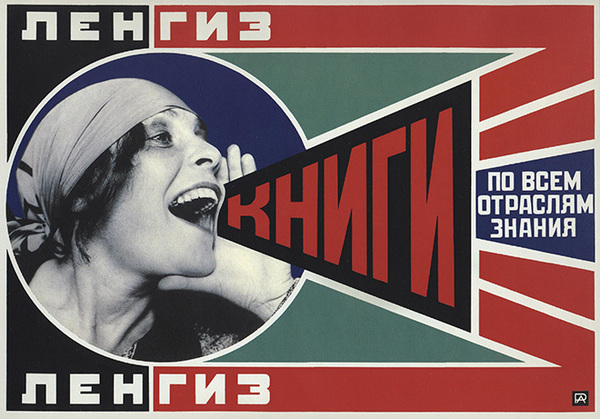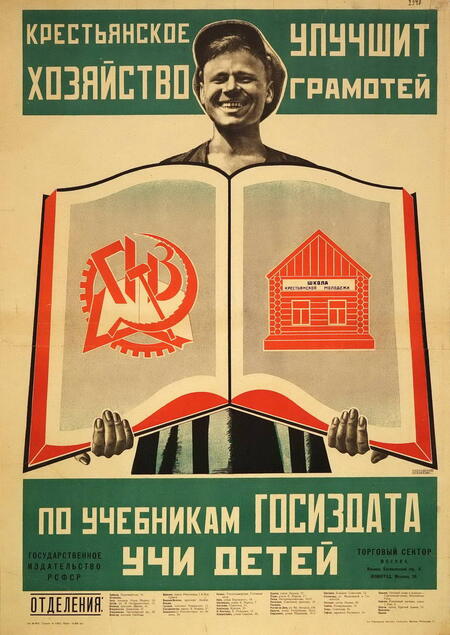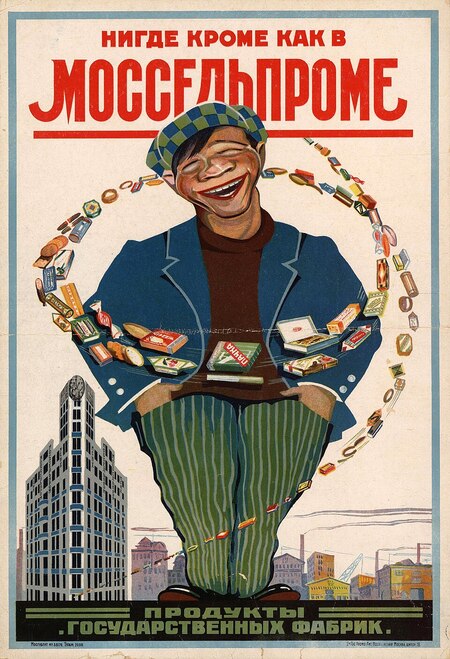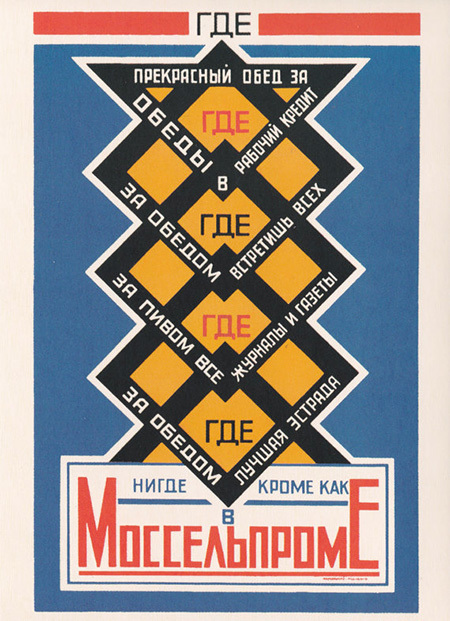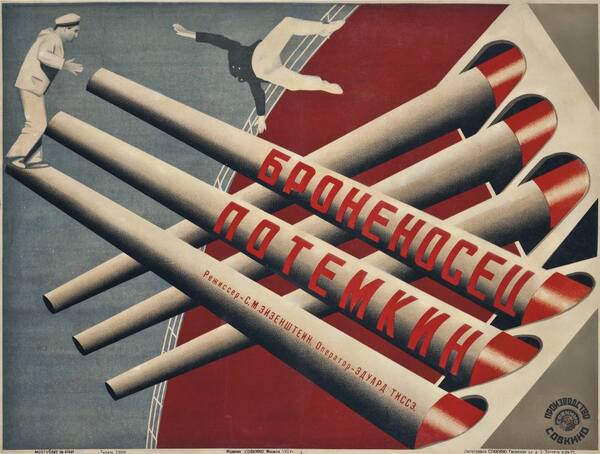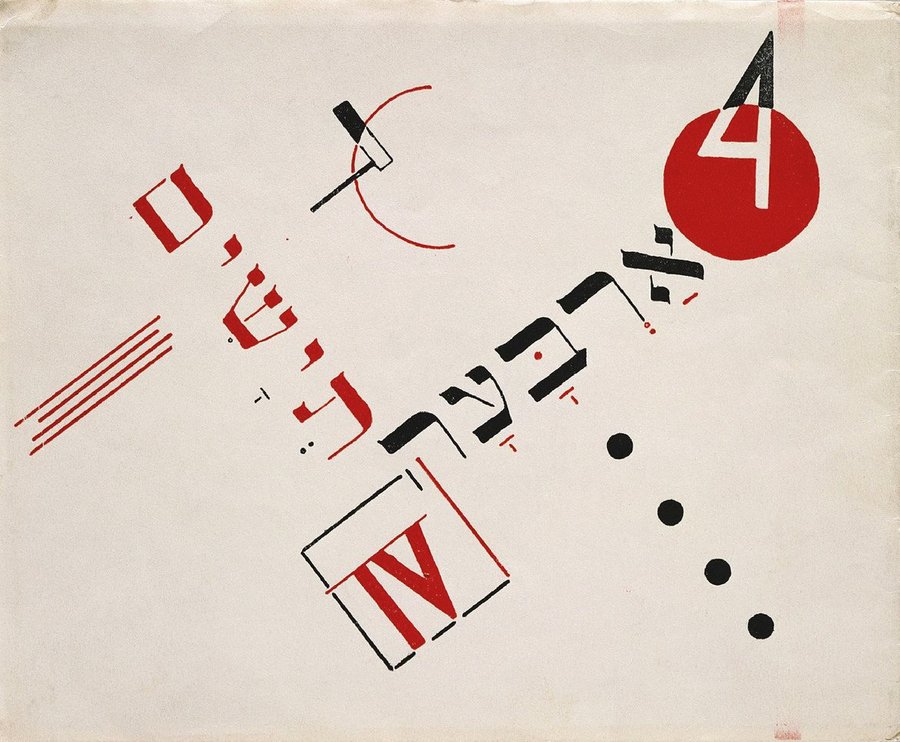
Красный шрифт: графика советского конструктивизма 1920-х гг.
[1] Введение
Эль Лисицкий, Teyashim (Four billy goats), 1922 год
После Революции 1917 года в России сформировалась потребность не только в новом политическом строе, но и в принципиально ином визуальном языке, способном отразить идеи строительства социалистического общества. Конструктивизм, возникший как авангардное художественное течение, стал ответом на этот социальный запрос, трансформировавшись из эстетического эксперимента в мощную систему графической пропаганды. Это направление радикально порвало с декоративностью предшествующих стилей, провозгласив функциональность и утилитарность главными критериями искусства. Данное исследование направлено на комплексный анализ того, как базовые принципы конструктивизма (функциональность, геометричность форм и инновационная типографика) сформировали уникальный визуальный код, определивший лицо советской графики 1920-х и начала 1930-х годов.
Актуальность темы подтверждается сохраняющимся влиянием конструктивизма на современный дизайн, что позволяет исследовать универсальные механизмы создания эффективных визуальных коммуникаций.
Основной исследовательский вопрос заключается в выявлении методов, позволивших конструктивистам создать столь эффективную систему визуальной коммуникации, способную транслировать сложные идеи нового общества массовой аудитории. Выдвигается гипотеза о том, что эта эффективность была достигнута благодаря органичному синтезу типографики, фотомонтажа и цветовой символики в единую систему графических кодов, превратившую плакат в мощный инструмент массовой пропаганды и социальной инженерии.
[1] Александр Родченко, Ленгиз: книги по всем отраслям знаний, 1925 год; [2] Александр Родченко, Обложка журнала «ЛЕФ» № 3, 1923 год
Исторический контекст исследования охватывает период Новой экономической политики (1921–1928 гг.), когда происходил расцвет конструктивистского дизайна. Именно в эти годы сформировался специфический спрос на рекламу, агитационные плакаты и оформление новой городской среды. Художественные институты, в частности ВХУТЕМАС, стали настоящими лабораториями нового искусства, где разрабатывались и апробировались революционные визуальные стратегии.
[1] Александр Веснин, Проект оформления здания ВУХТЕМАСа к 10 годовщине Октябрьской революции (эскиз), 1927 год; [2] Неизвестный автор, Фрагмент обложки журнала «Техника и жизнь № 6», 1925 год
Отбор материала для исследования основан на принципе репрезентативности — в фокусе внимания находятся канонические работы ключевых представителей движения: А. Родченко, В. Степановой, Эля Лисицкого, братьев Стенбергов. Их творчество наиболее полно отражает основные тенденции и художественные открытия эпохи. Особый акцент делается на тех произведениях, которые стали визуальными манифестами своего времени и оказали значительное влияние на развитие всего мирового графического дизайна.
[1] Варвара Степанова с мужем Александром Родченко, Неизвестный год; [2] Эль Лисицкий за работой над макетом оформления спектакля «Хочу ребенка», 1928 год; [3] Братья Стенберги, Неизвестный год
Методология исследования строится на принципе декомпозиции визуального языка на составляющие элементы. Структура работы включает анализ теоретических основ конструктивизма, исследование типографики как инструмента идеологического воздействия, изучение фотомонтажа как нового способа визуального высказывания, рассмотрение киноплаката как синтеза различных художественных практик и, наконец, рефлексию о наследии конструктивизма в современной визуальной культуре. Каждый раздел демонстрирует, как конкретный художественный прием работал на решение идеологических задач нового общества.
[2] Теоретические основы конструктивизма
Теоретики конструктивизма провозгласили отказ от искусства как украшения жизни. В своей работе Алексей Ган утверждал, что творчество должно стать способом организации новой материальной среды, отражая классово-пролетарский подход к построению общества. Художник в этой системе становился инженером, конструирующим полезные вещи для повседневного быта.
«Искусство в производство»
Алексей Ган, Конструктивизм, 1922 год
Влияние производственного искусства
Идеи теоретиков производственного искусства, в частности Бориса Арватова, о полном слиянии художественного творчества с промышленным производством, нашли непосредственное воплощение в графике. Плакат или обложка книги начали восприниматься как промышленные изделия, несущие конкретную социальную функцию и утилитарную ценность.
[1] Елена Худякова в спортивном костюме по эскизу В. Степановой, 1985 год; [2] Варвара Степанова, Эскизы спортивного костюма в журнале «Леф» № 2, 1923 год
Социальная функция дизайна
Конструктивисты рассматривали дизайн как инструмент социального преобразования. В отличие от прежних художественных течений, они стремились не к созданию уникальных произведений, а к разработке типовых форм, способных массово внедряться в жизнь и формировать новое, социалистическое сознание.
ЛЕФ № 2, 1923 год